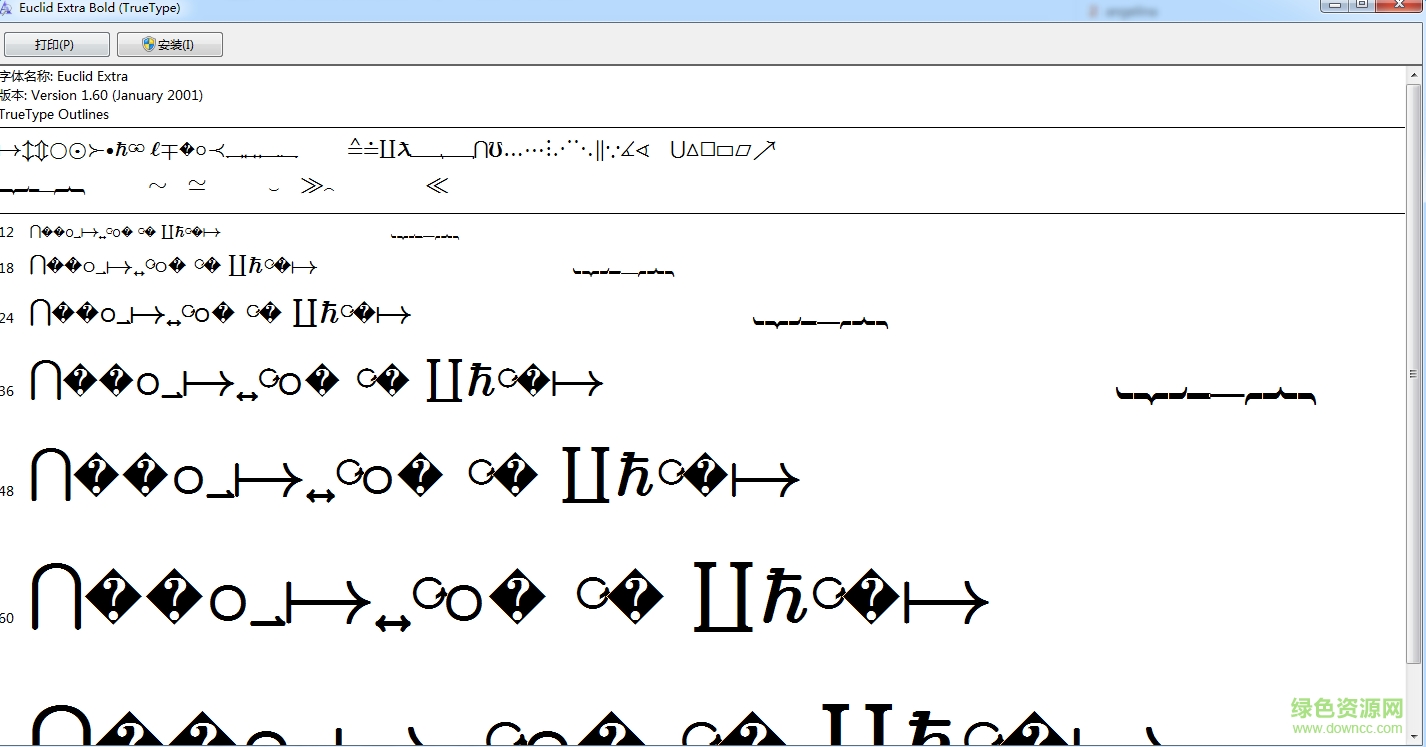
euclid extra字體是一款專業(yè)的計(jì)算機(jī)數(shù)字矢量字體,word公式中就用到了這款字體,有的時(shí)候軟件沖突或誤刪文件可能導(dǎo)致公式顯示亂碼,符號(hào)無法完整顯示,大家可以在本站重新下載該字體安裝使用!
真正的所見即所得字體。由于euclid extra字體支持幾乎所有輸出設(shè)備,因而無論在屏幕、激光打印機(jī)、激光照排機(jī)、公式編輯器上,還是在彩色噴墨打印機(jī)上,均能以設(shè)備的分辨率輸出,因而輸出很光滑。